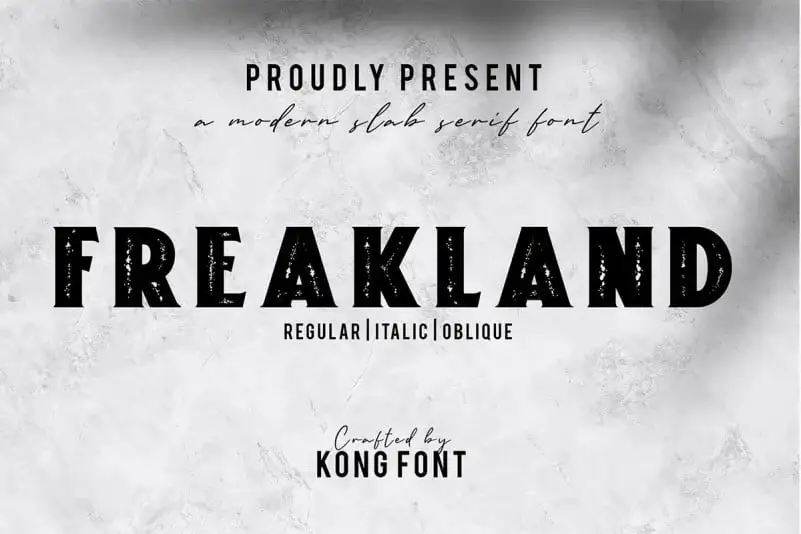
Freakland Display Font – Download Grátis
A Freakland Display Font é uma escolha perfeita para designers que buscam um estilo moderno com elementos serifados, mantendo a sensação de letras maiúsculas. Seu uso predominante das letras maiúsculas proporciona uma disposição clara e equilibrada, ideal para destaque em headlines ou logos. Esta fonte é especialmente adequada para aplicativos variados como rótulos de embalagens, materiais publicitários em formato de pôster, camisas personalizadas e mais. Seu design moderno inclui números e pontuação, permitindo uma ampla gama de opções de design. Composta inteiramente em letras maiúsculas, esta fonte é perfeita para expressar identidades visuais fortes e assertivas em projetos que valorizam o uso de letras completas. Não importa qual tipo de projeto você está planejando, a Freakland Display Font fornecerá uma solução elegante e versátil para destacar seu trabalho gráfico.